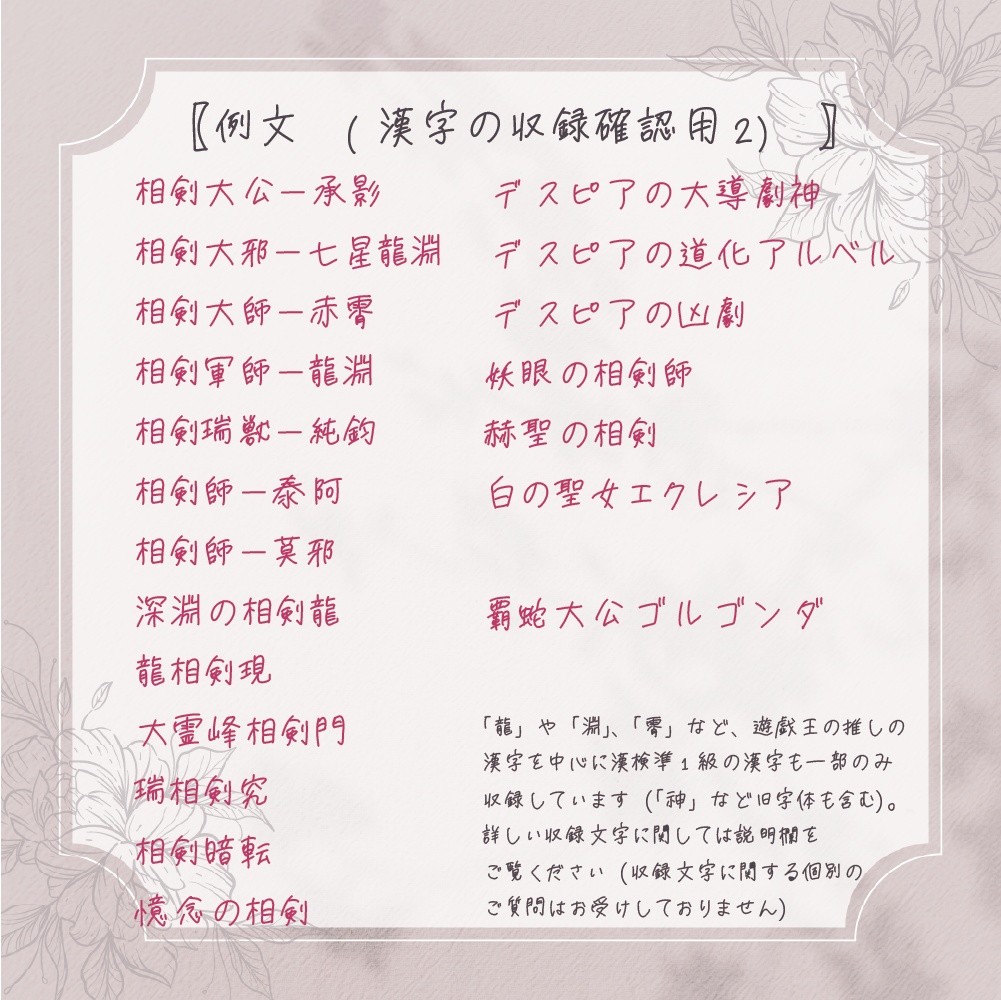
【有料フォント】OLナハトさん改(OLNacht-sanG/B)【ウェイト2種類】
https://nacht-7810.booth.pm/items/4928202 こちらのフリーフォント『OLナハトさん』を改良した有料フォントです。 VTuber兼デザイナーの湊月ナハトの手書き文字で制作した、 優しく読みやすい(?)大人の女性による手書き風フォントです。 アルファベット(半角・ウムラウト等も対応)・ひらがな・カタカナ(全角)・数字・記号に加えて、 小中学校で習う常用漢字+430字程度の漢字を追加収録しています。 ■収録文字 ひらがな・カタカナ(全角) アルファベット(半角・一部記号・ウムラウトなど対応) 数字(半角) 漢字:小中学校で習う範囲+準1級を中心に約430字追加(一部旧字体あり) ■ファイル内容 ・OLNacht-sanG.ttf(細字) ・OLNacht-sanG_B.ttf(太字) ※TrueTypeフォントファイル(.ttf)です。 フォントファミリーには対応しておりませんので、2つ別のフォントとしてインストールされます。 ■商用利用に関して 個人利用に限り可。1回のご注文につき、お1人分ご利用いただけます。 データの複製、改造、再配布、サーバーへのアップロード等は禁止とさせていただきます。 (※法人での使用はご相談ください) ■おすすめの使い方 ゆるめの雰囲気が欲しい同人誌・動画・DTP、WEBデザイン・サムネイルに 学校や教育系コンテンツとの相性も◎ 推しのスクリーンショットに添える一言などにもぴったり! 手書きフォントの特性上、字によってはクセやゆれ、 あえての崩し(小さい・はみ出し等)があります。 そうしたラフさやゆるさを楽しめる方におすすめです。 ※このフォントは「iFontMaker」というアプリを使用して制作しました。 ■収録文字(追加分)※Ctrl+Fで検索できます(PC版)。 楠莉胡逢樽凛鞠瑞霄湊龍淵神豫頰拜拜攜讓歡獵歡觀讚驗臟勸豐辭觀覽覽覽歡錄讓讓讓觀觀臟臟獵鈞莫阿礼阿槌沌蘇縋冀赫云乃卜叉巳勺之也丑勿仇尤巴什壬匁廿允疋弗禾叶凧弘戌汀仔只乍叩卯亘牟托伍此瓜亥凪弛而吃吊肋亦伊汐曵尖匡咎尖蝦夷牝扶丞舛圭汝卿旭庄佃呑牡扮苅李酉庇緋辰杖枷砥伽杏吾坐冴兎呑芥灼芙蓉吻劫牢汲灸吠吼迂宋其怯姑怯斧狛狗胞朋妾姐昂昏函沫頁荊穿茜謀叛珊瑚姪剃屍狐殆杯盃歪烙姦廻巫訃亮垢竿狼耽溺栗隼釘紐狸紗脆倶戴珪藻晃哨閃紘峰鴉烏焔鳳凰桶兜袴葡萄薔薇稀悶甥褥喋蜘蛛蛙萩椿袈裟蛸詫煽飴綴漕鞄蝿蝶蝉蝕髭鬣窺諜頸椎叡錆諌諫籠篭鞘儘唾燕頓縞繋鮭癌趨鞭鯉鯖蟻轟轡鷹鷲鱗鹸讃纏餐鰻瀞贋襖叢薮糞鮫膿聊鍔醗酵犀穎蕩蕊麹辟錯灌漑腿隙厭嘘溜蓮罫啜壺覗智匙躯軀躰悉釦鈕梱淘汰渕娼掻髑髏挽脆凋咳烹碍箋愕鋲頓澱謬鎚濯綺羅彙朧峻崚澪漣渚潤瑛瑠璃翠稜嵩嶺崖鍾馴璧瓊瑣慄憬憧怜惇惟惚惹愉愁慨憂慧憫戚摯捺揃擢撫曖昴暉曽朔朕朦朋橘檀檬檸檎櫛櫓殉殯毅洵湧滉澄瀧瀟瀬熙燦燈爛珂珈瑚瑤璋甄畏畢疇瞭瞳礁禎禍禪禱秤稟稽穣竣竪篠篤簾籐緻縷纓缶羨羯翁聡肇臥舷艶蕉艸莞蒐蒲蕨蕎蘭蠢衷裟覇訣諒諧諱謳譜讐貰趙躊躇輔輿轍辻迦邂鄙酌酎醍醐醤釉鈍鉦鋳錠鍬鎧鑓霙霞頌顰騰髄鬱鯵鯛鯱鰯鰹鱈鱚鱧鳶鵬麒麟黍黎黛體變舊讀囘澤壞壓彥齋靈醫藝關齒戀辯辨證實獻壽德澁舖齊總黑鹽歷縣實歷醫關